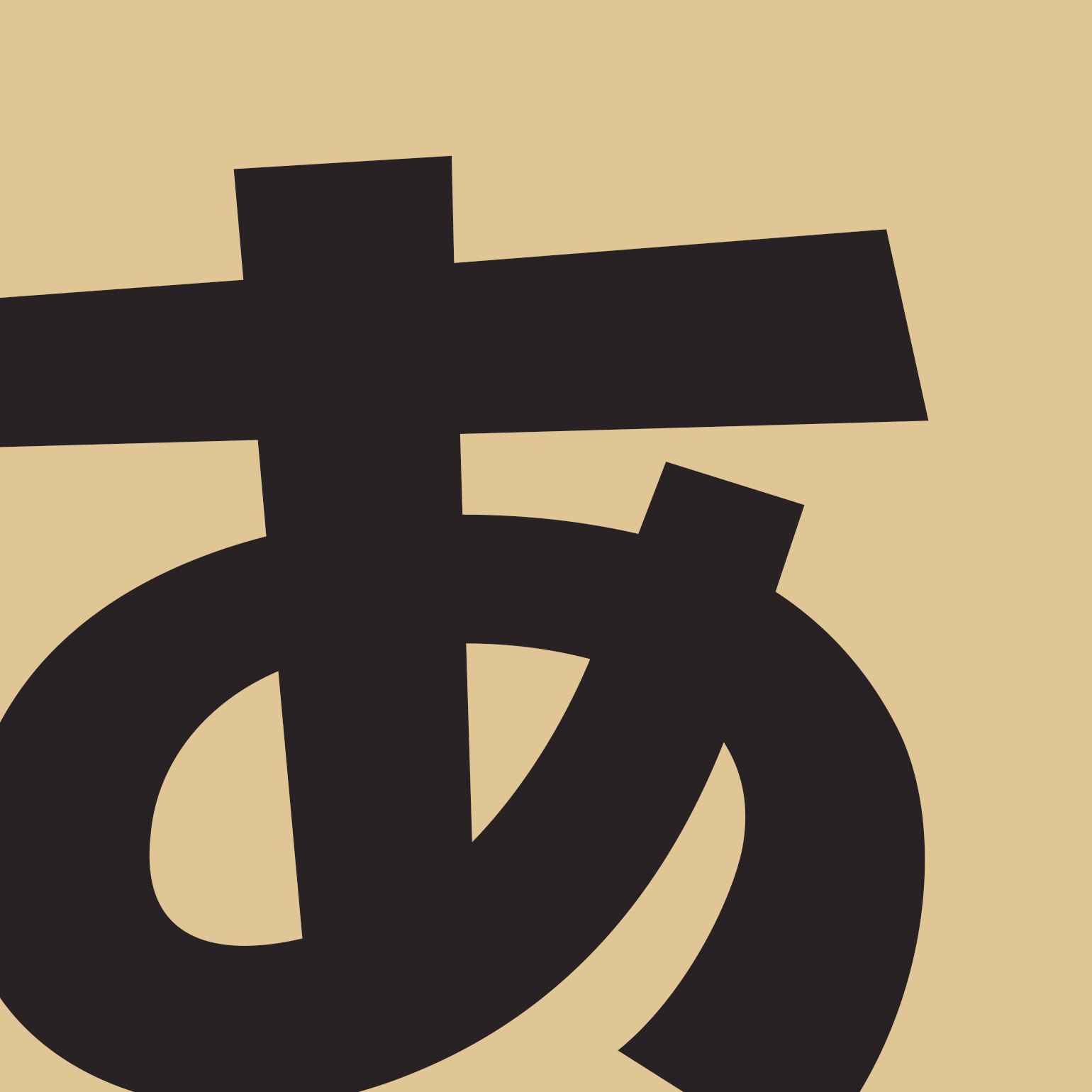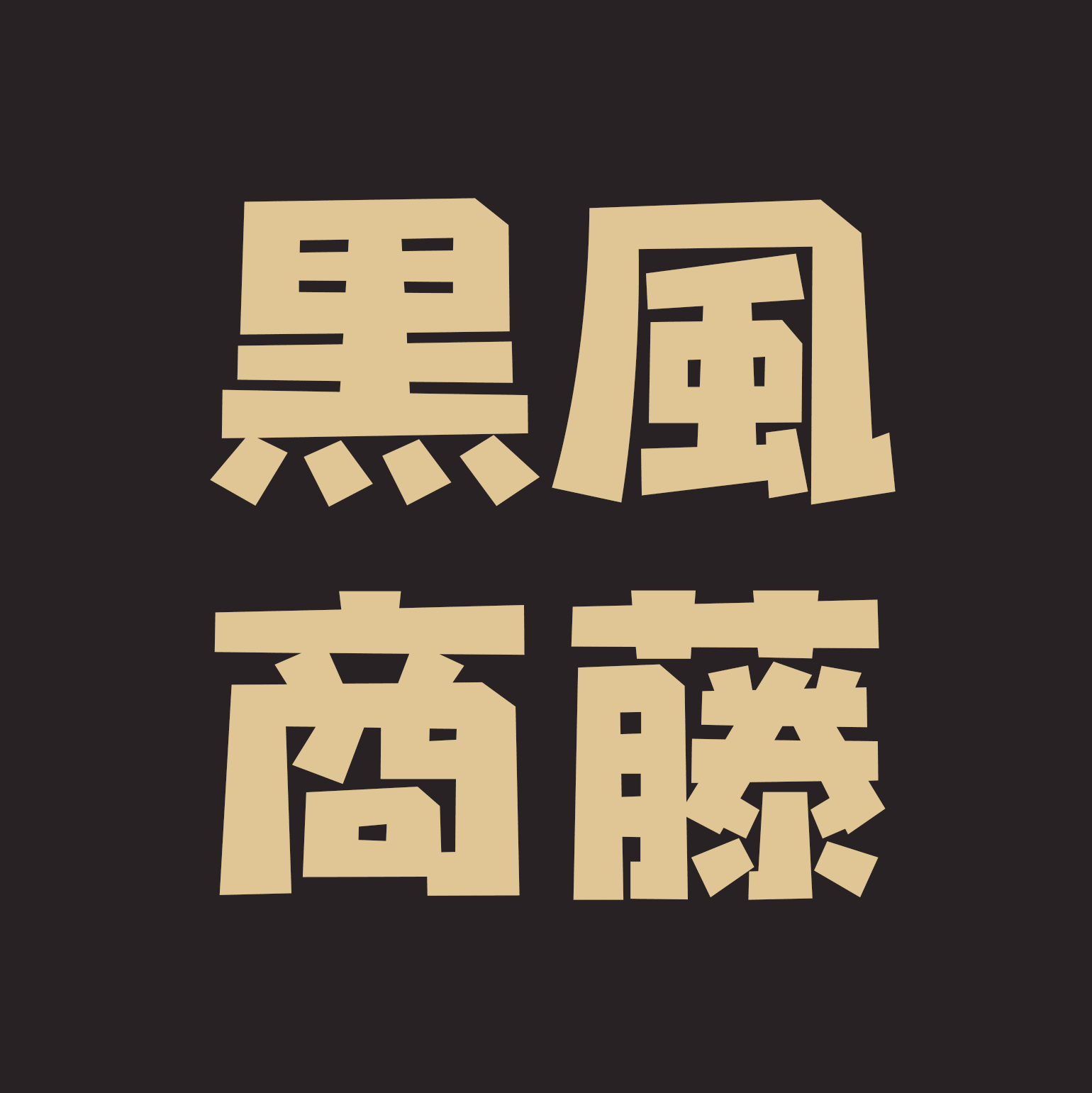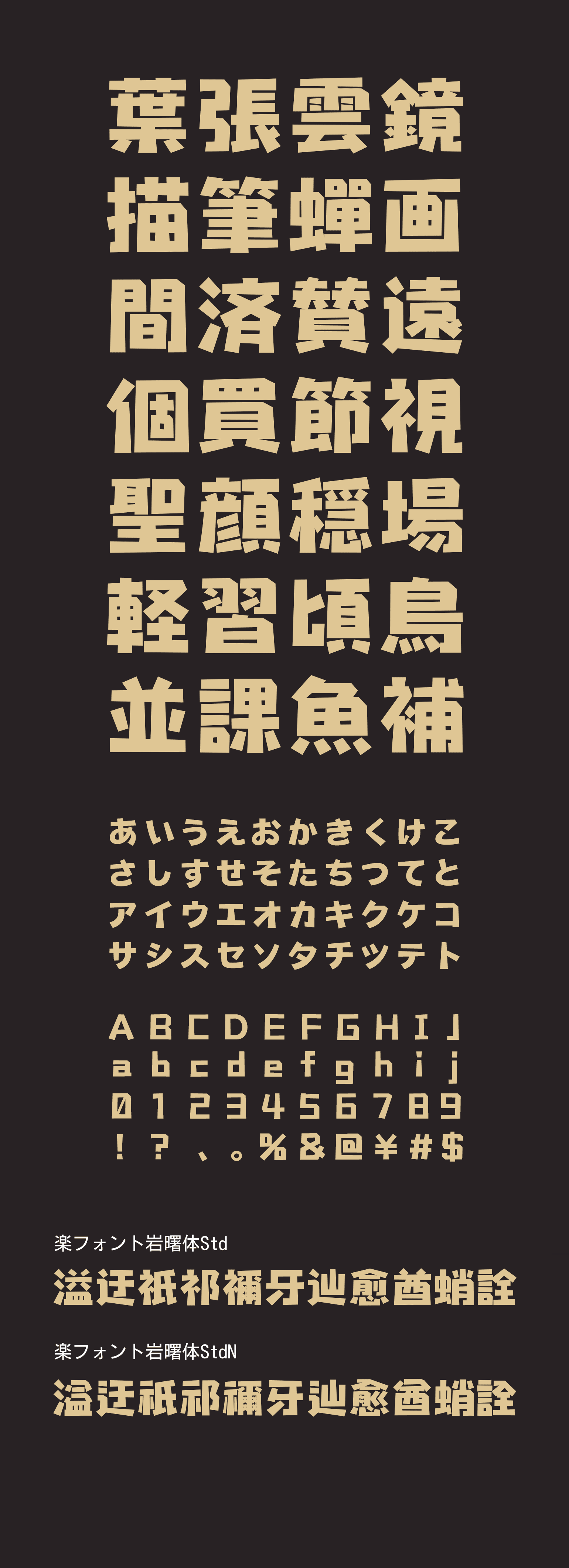
岩曙体(がんしょたい)
オーソドックスなゴシック体を基調としながら、字画の角を落とした形が特徴的な書体は薄闇から顔を出す朝日で 輪郭が欠けて見えている山岩を意識しています。 自然をもとにした形状は雰囲気が素朴ですが、 長い時を経ても不動の岩をモチーフにした形状は抜群の安定感があり、飽きが来ません。 硬派な印象を与えることもさながら、ポップでキャッチーなシーンでの使用にもおすすめです。